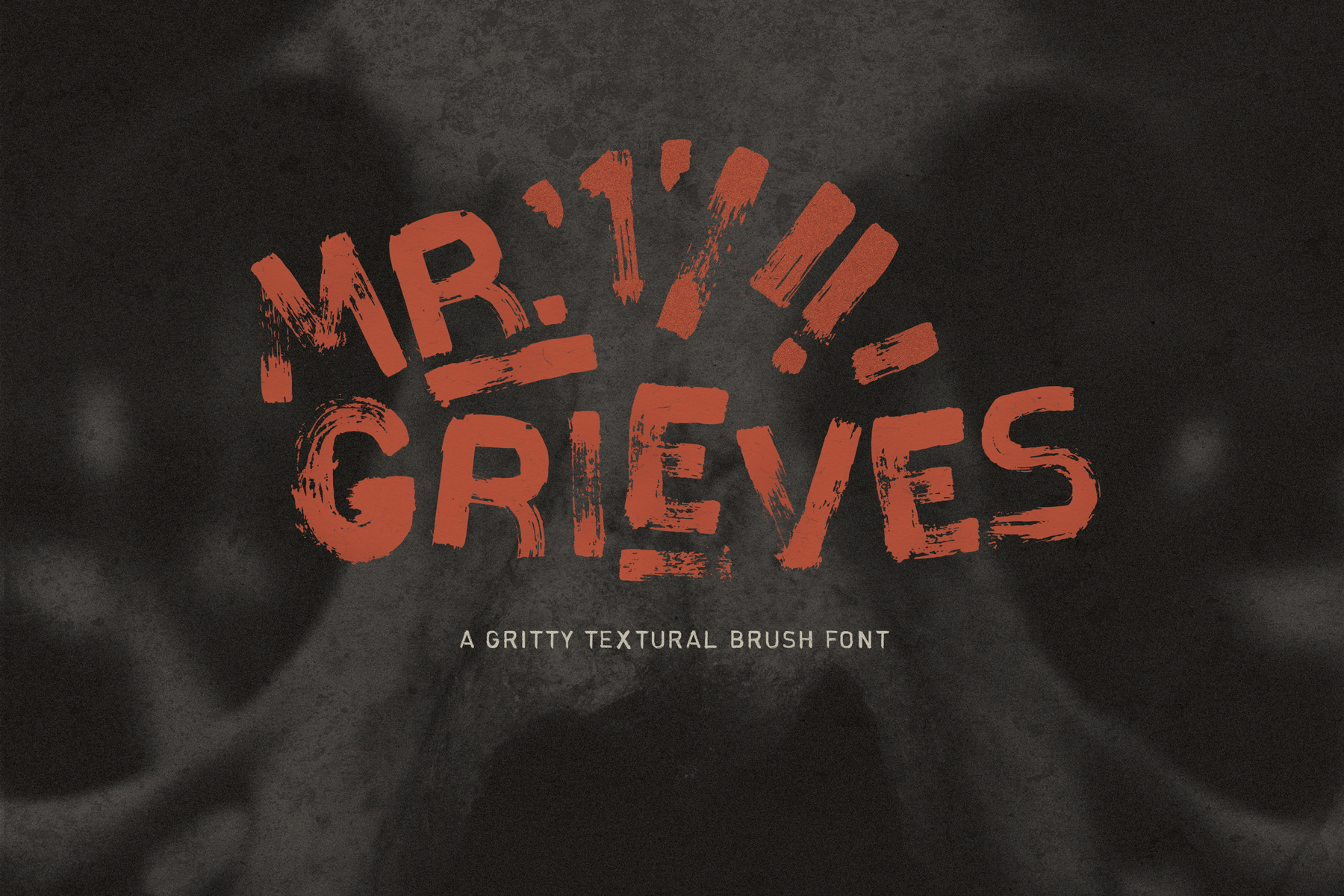
Mr. Grieves Brush Font – Download Grátis
A fonte ‘Mr. Grieves Brush Font’ é uma escolha perfeita para qualquer projeto que exige uma aparência natural e envolvente. Desenvolvida pela designer Jennyfox, esta fonte tipo sans-serif traz uma textura artesanal com suaves traços de pincel. As letras maiúsculas são elaboradamente renderizadas à mão, com borrões de tinta abundantes e texturas grossas que criam um estilo único. Embora seja bastante minimalmente editada, cada caractere mantém sua integridade autêntica. Seu design perfeito para uso em exibição cria uma atmosfera agradável e natural na página do seu projeto. Perfeita tanto para aplicações digitais quanto impressas, ‘Mr. Grieves Brush Font’ é um recurso gráfico indispensável para quem deseja incorporar elementos únicos de arte digital no design de sua marca ou conteúdo.
Designer: Jennyfox